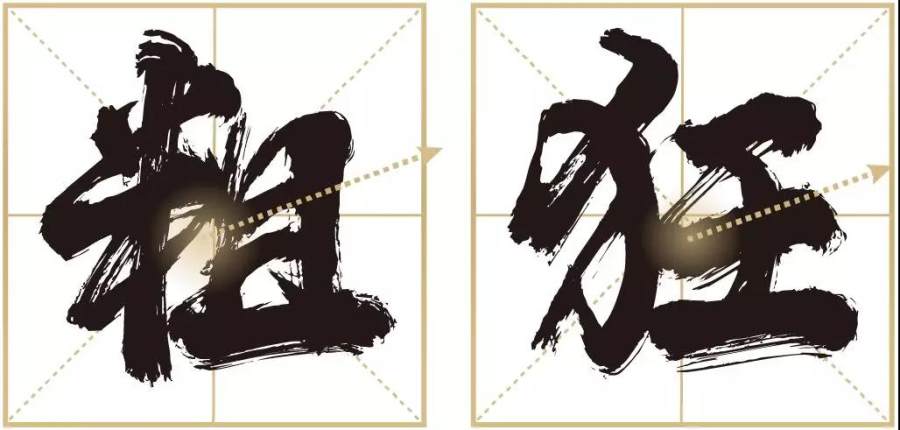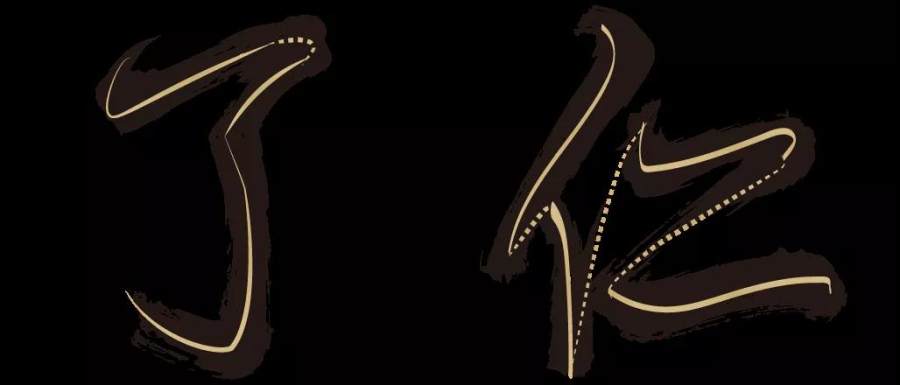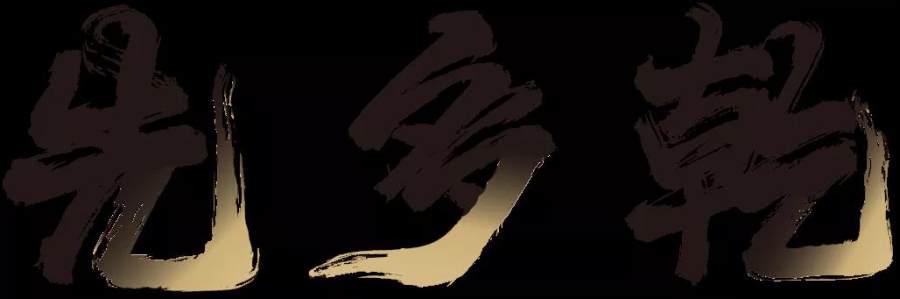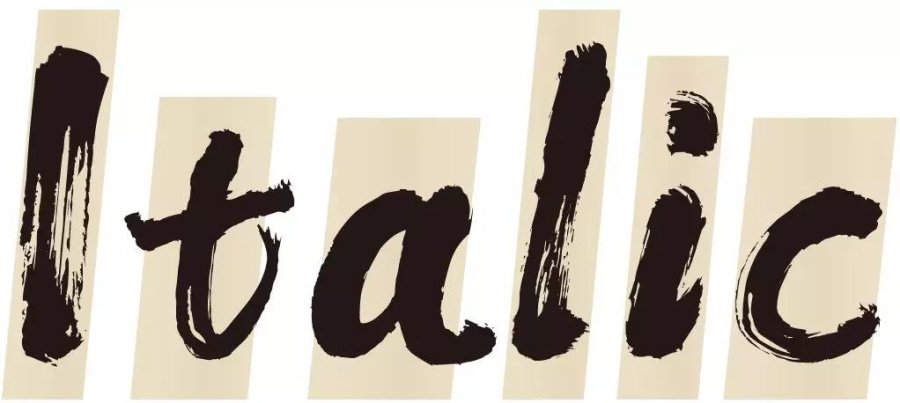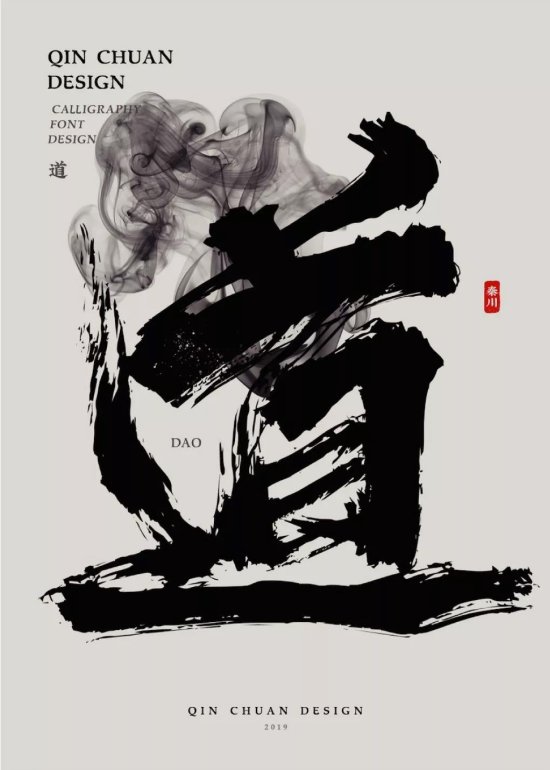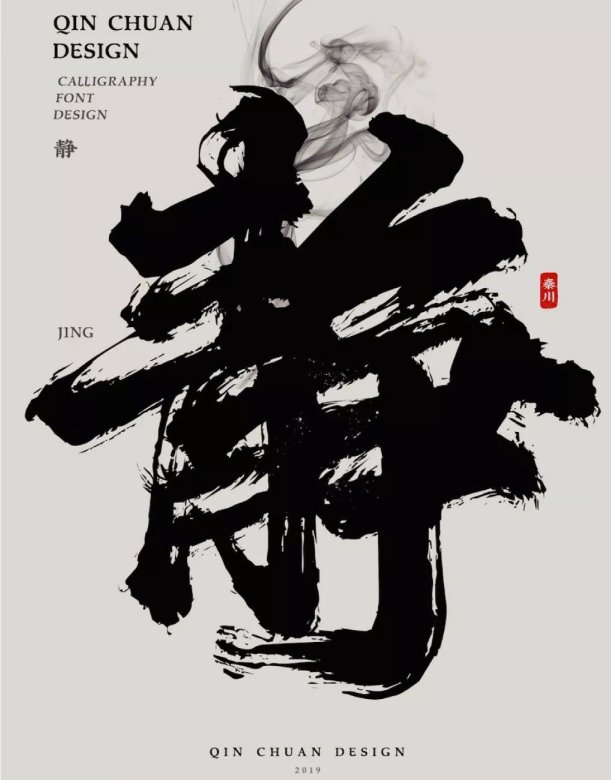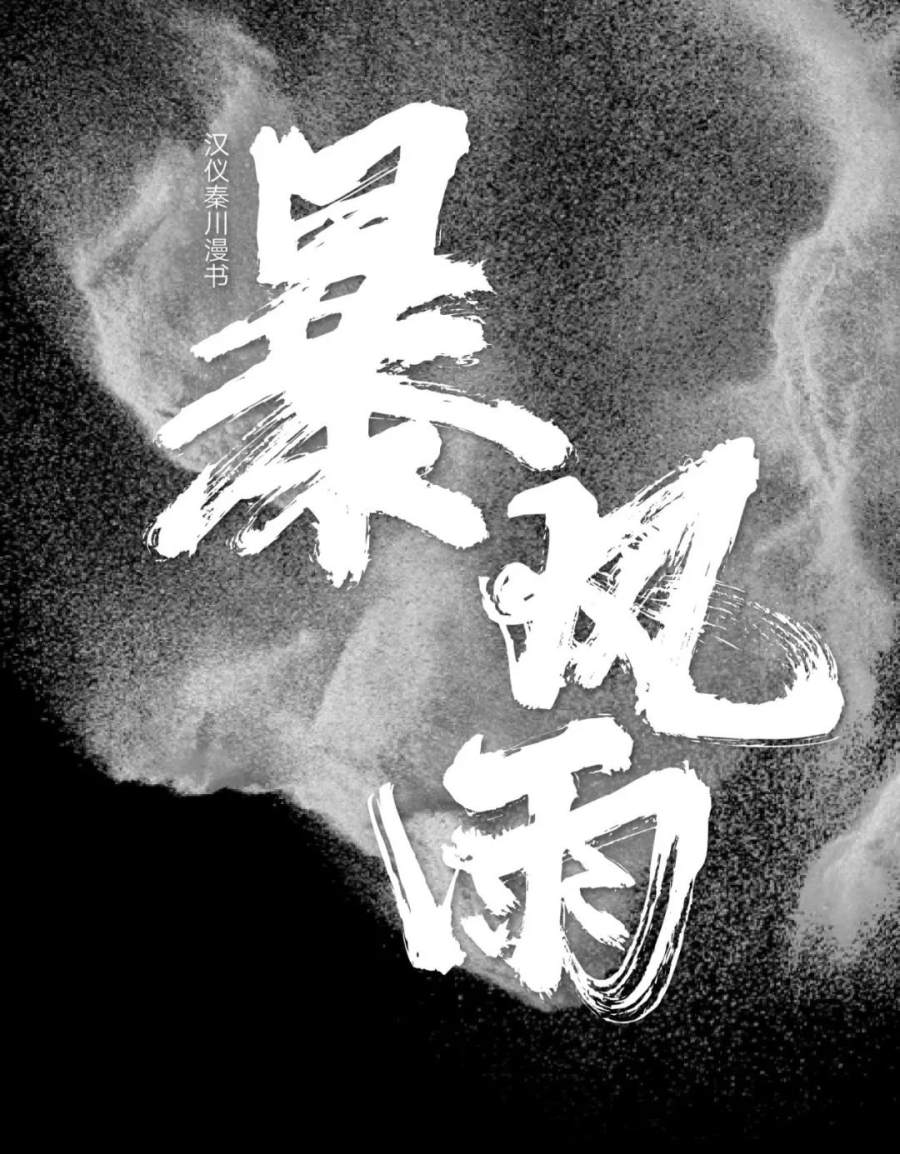
汉仪秦川漫书 | 字形特点
汉仪秦川漫书,字体字形均向右上方倾斜,与水平方向形成一定倾角。
结构严谨,笔画链接流畅,气势顺达。
汉仪秦川漫书 | 飞白笔画
汉仪秦川漫书笔画丝丝露白、笔道清晰、翻转明显。
断断续续的飞白连笔增强了字体的呼吸感,在虚实和粗细的对比下效果更加震撼,
增强了字体的节奏感和韵律感。
汉仪秦川漫书 | 强劲张力
汉仪秦川漫书笔画粗壮豪放,撇捺张扬,尾部的甩尾有力且有丰富的笔触细节,空间感十足。
汉仪秦川漫书 | 西文字母
汉仪秦川漫书的西文字母以意大利斜体的风格为基础,结合部分中文笔画特征,线条流畅,手写感强。
汉仪秦川漫书 | 应用展示
汉仪秦川漫书,笔画较粗,整体风格比较稳重,
可以作为标题字被广泛应用于多种场景
如游戏动漫、影视、杂志封面及产品包装等。